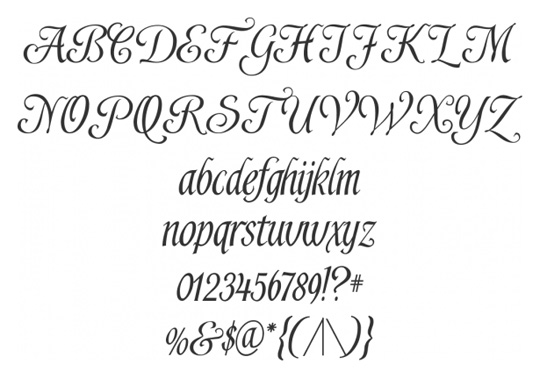
Как подобрать правильный шрифт для своего дизайна
Дизайнеры очень часто не уделяют должного внимание типографике, когда на самом деле — это очень важный аспект, от выбора которого нередко зависит качество дизайна. Шрифты так же важны для веб-сайта, как и изображения.
Типографика — это не просто выбор шрифта. Это также этап, на котором необходимо задумать о кернинге, трекинге и интерлиньяже. Частью типографики также является выбор цвета текста, расположение текста и даже дизайн страницы.
Эффективность сообщения, которое вы хотите передать своим сайтом, часто зависит от выбора гарнитуры. Хороший шрифт завлекает зрителя и влияет на его восприятие идеи.
Хорошо подобранный шрифт помогает зрителю получать удовольствие от чтения. Необходимо всегда выбирать шрифт к подходящей ситуации.
Выбор правильной гарнитуры также усложняется тем, что доступных для использования шрифтов очень много. Нельзя сказать, что есть какое-то определенное правило, помогающее подобрать правильный шрифт во всех случаях, но есть некоторые принципы, которые могут быть использованы в самых различных ситуациях и достойны дополнительного внимания.
Разборчивость очень важна
Для того, чтобы читающий мог понимать о чем идет речь, очень важно чтобы гарнитура была разборчивой. Существует множество факторов, которые необходимо учитывать, когда дело касается разборчивости текста. Эти факторы включают в себя размер, форму и ширину символов, визуальный веc, надстроечную и подстрочную длину, а так же контрастность штриха. Выбор качественного шрифта – хорошее начало для создания разборчивого текста, но из-за огромного количества различных шрифтов выбор сделать может быть очень непросто.
Определенные элементы текста могут показаться посетителям сайта выделенными, если изменить высоту или визуальный вес шрифта. Helvetica Neue например имеет не только жирный и курсивный, но и тонкий и ультра-тонкий. Такие шрифты очень полезны, если хочется сделать дополнительный акцент на гарнитуре сайта.
Самые понятные шрифты — те буквы у которых имеют привычную форму и общее характеристики которых наиболее постоянны. Для того чтобы шрифт казался пропорциональным приходится регулировать расстояние между символами – этот процесс называет кернингом.
Таким образом улучшается вид шрифта в целом.
Качественные гарнитуры всегда разбиты на керн-пары позволяющее легко достигнуть нужного эффекта. Расстояние между буквами очень влияет на разборчивость шрифта, поэтому шрифты со слишком большими расстояниями между символами стоит избегать.
Самый часто задаваемый вопрос при выборе шрифта: с засечками или без?
Самые распространение категории шрифтов – это serif или sans serif. Serif – это шрифты с заческой на концах букв. Sans serif же, соответственно — шрифты, которые засечек не имеют.
Классифицировать эти шрифты не просто, так как и тех и других шрифтов немало. В целом, serif считаются более традиционными, а sans serif — современным. Serif шрифты иногда также считаются более четкими и легкими для прочтения.
Огромное количество хороших шрифтов существует и в той, и в другой категории. Можно намного лучше начать понимать шрифты, изучая различные классификации, такие как humanist, modern, slab serif, geometric, old style и transitional.
Некоторые дизайнеры даже советуют создавать свои собственные категории для удобной работы с различными проектами.
Выбираем правильный шрифт для веб-сайта и используем их правильно
Очень важно чтобы типографика привлекала зрителей и сохраняла их внимание, поэтому шрифт должны легко читаться, быть приятными и аккуратным. Заголовки и подзаголовки должны привлекать внимание, а сам контент может быть выделен определенным образом с помощью курсива, жирного шрифта цвета или положения шрифта.
Размер шрифта тоже имеет не малое значение и этим фактором не стоит пренебрегать при создании дизайна веб-страницы. Стоит отдавать предпочтение более крупному шрифту, так как его проще читать при маленьком разрешении экрана, с планшетов, смартфонов и ноутбуков.
Текст и фон также не должны сливаться. Если фон темный, то шрифт должен быть светлым и наоборот. Это гарантирует разборчивость текста и таким образом вам будет проще донести смысл текста.
Комбинирование различных гарнитур также может быть очень эффективным.
Важно помнить, что шрифты должны быть достаточно различны, чтобы необходимый эффект был достигнут. Хорошим выбором будет один шрифт serif и один шрифт sans serif. Это создает контраст, который придает тексту слаженность, особенно, если это шрифты одного и того же дизайнера.
Выбор правильного шрифта для печати
Правильно подобранный шрифт поможет создать хорошее первое впечатление. Хорошо подобранная комбинация шрифтов поможет выделиться и запомниться. При этом не имеет значение печатный бланк ли это, визитная карточка или просто листовка.
Шрифт не должен перекрывать смысл текста, так как это отвлечет от информации, которую вы хотите передать. Цель гарнитуры – упростить чтение текста, и если перестараться то читатель будет смотреть только на шрифт, не воспринимая сам текст.